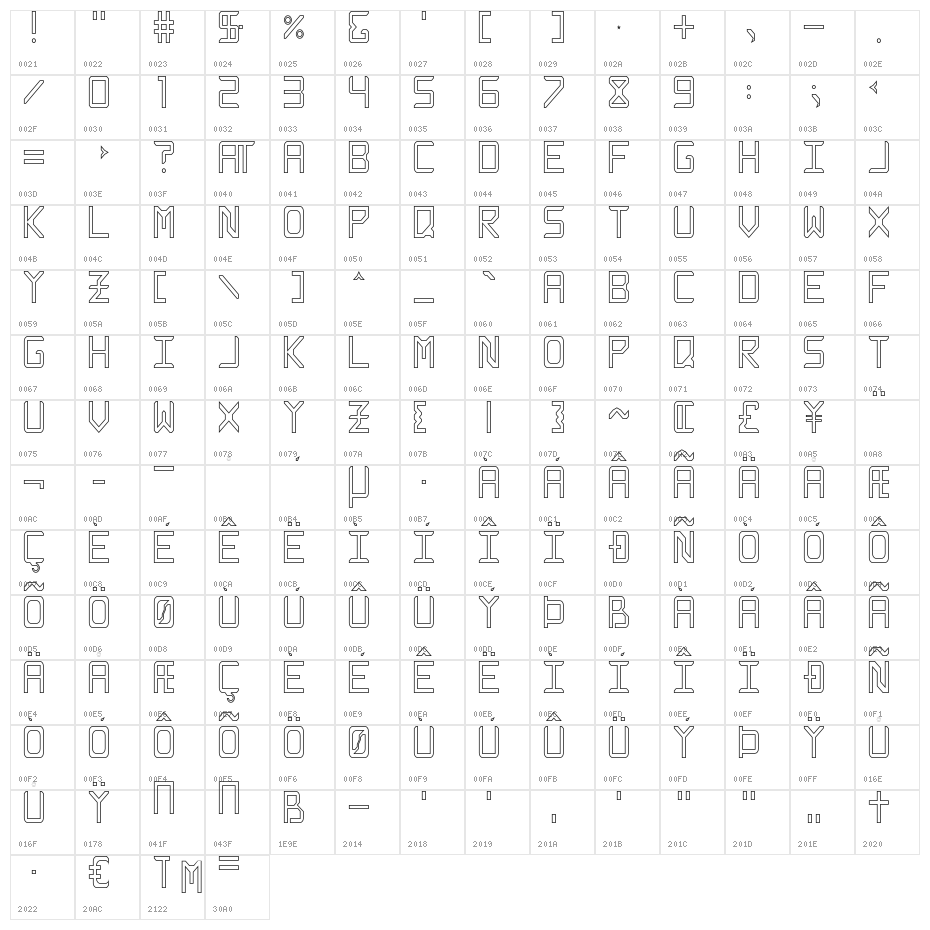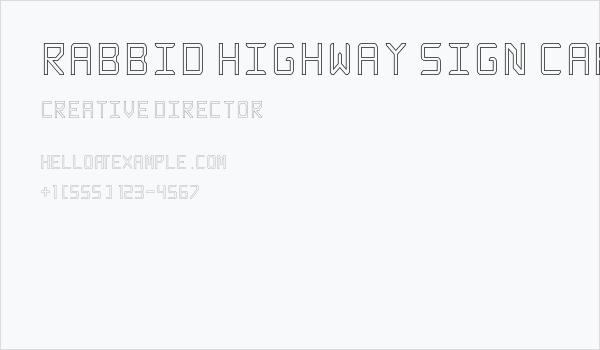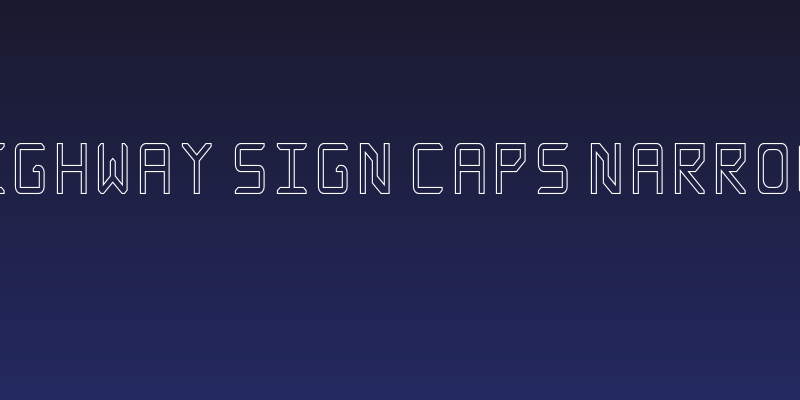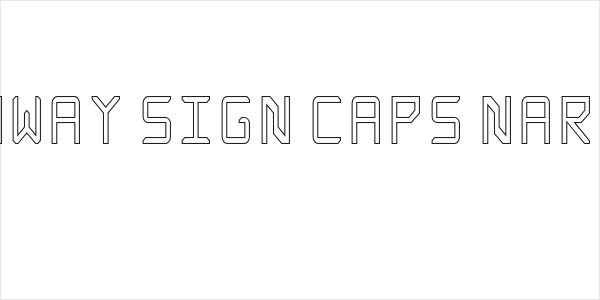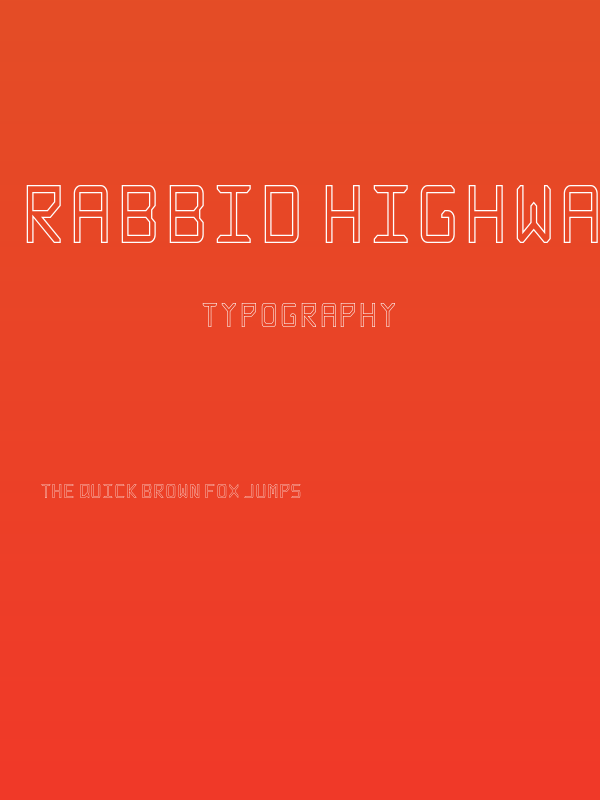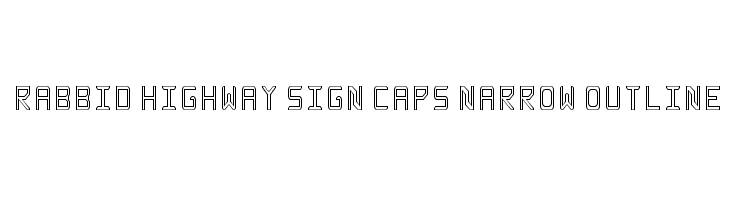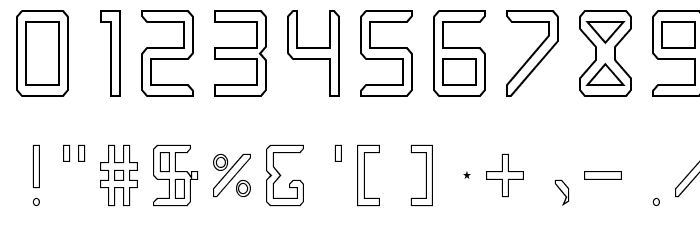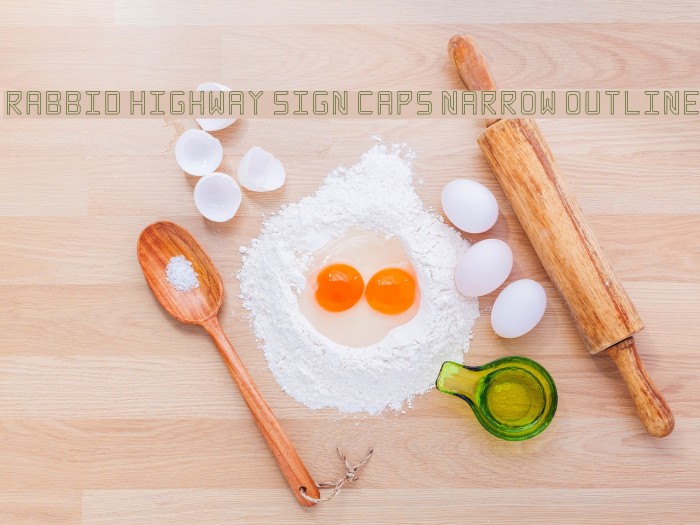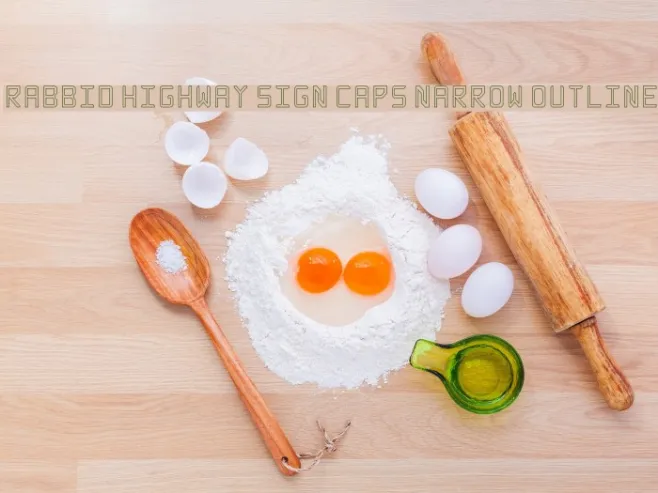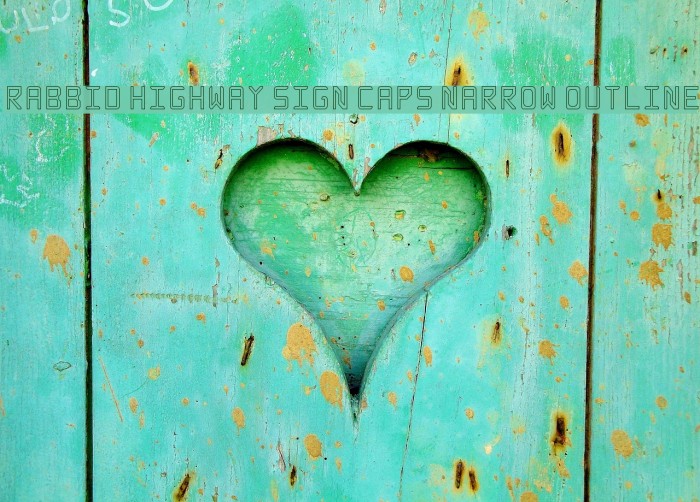
Rabbid Highway Sign Caps Narrow Outline Font
| Cas d'utilisation | Headlines, Logos, Signage |
| Projets proposés | Ideal for digital displays, highway signage, technical manuals, and futuristic design projects. |